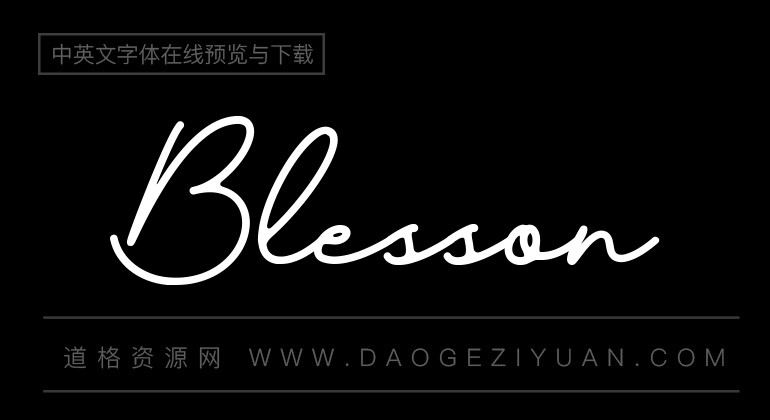
Blesson
Blesson 字体是一款简洁时尚的拉丁文字体,由葡萄牙设计师Joana Correia设计。它的特点是灵活的线条,明亮的色彩,以及明显的手写风格。它可以用于任何类型的印刷工作,特别适合用于标题,标签,海报,书籍,杂志,网站,品牌标识等。它可以带来简洁,时尚,优雅的设计效果,可以更好地表达设计师的意图。
Blesson是一款非常不错的手写艺术字体,具有很好的视觉感,适合于文化类的宣传设计、商业类品牌的广告和产品包装设计以及个性化文字排版等较多场景。
Blesson字符映射图